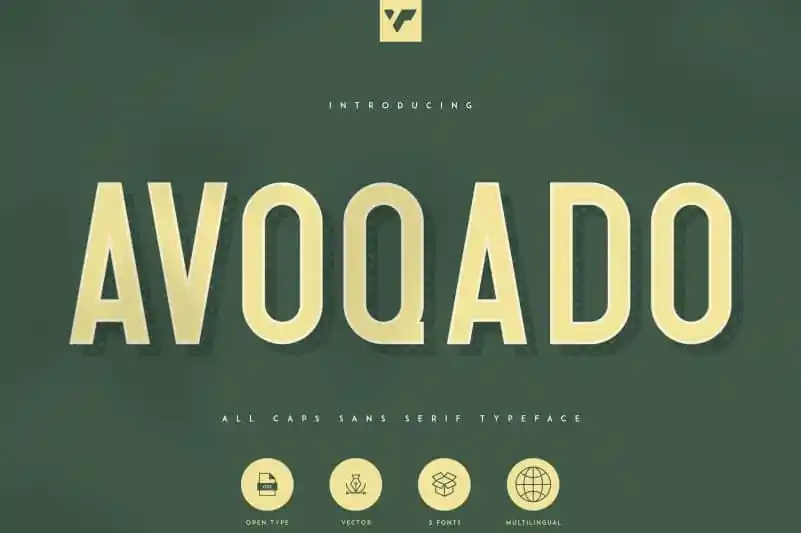
Avoqado – Sans Serif Font – Download Grátis
Avoqado é uma tipografia sans-serif que oferece uma experiência moderna ao mesmo tempo nostálgica. Com cinco estilos distintos disponíveis, essa fonte retrogama e bold pode transformar seu design de forma marcante sem perder a elegância necessária para um layout contemporâneo. A sua mistura única de simplicidade e força torna Avoqado uma opção perfeita para designers que buscam trazer algo inovador ao seu trabalho, sem deixar de lado a qualidade clássica da fonte sans-serif. Com Avoqado, você terá o poder de transformar qualquer projeto em um verdadeiro destaque no ambiente digital.